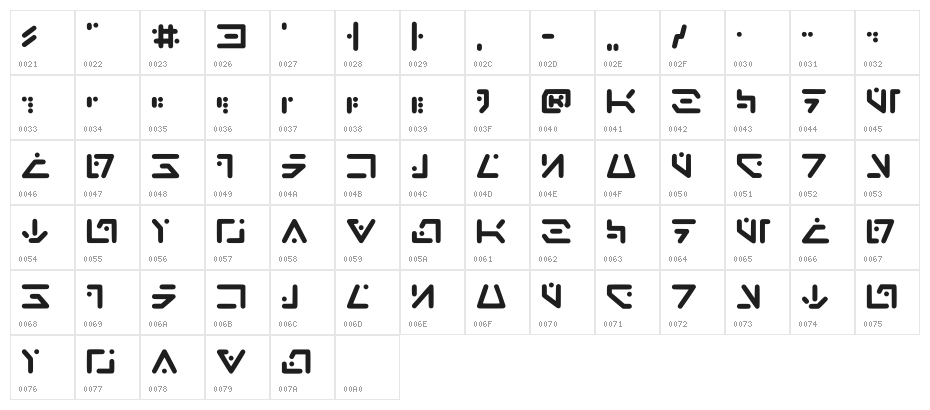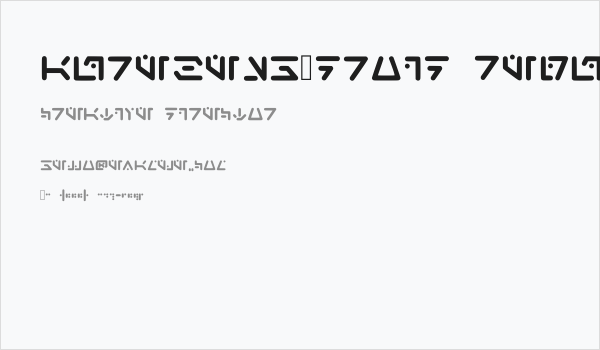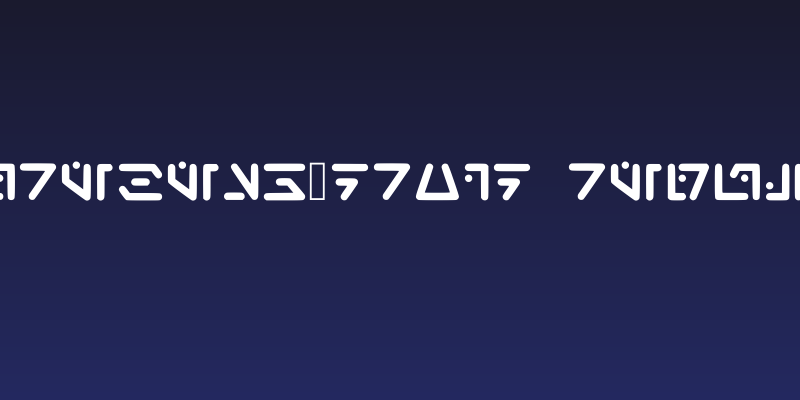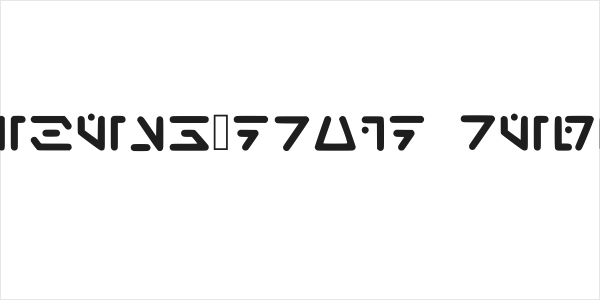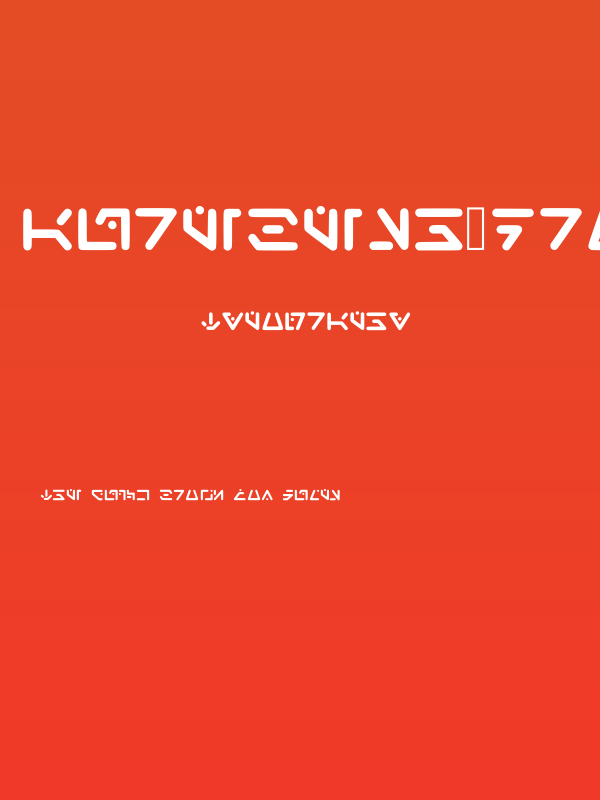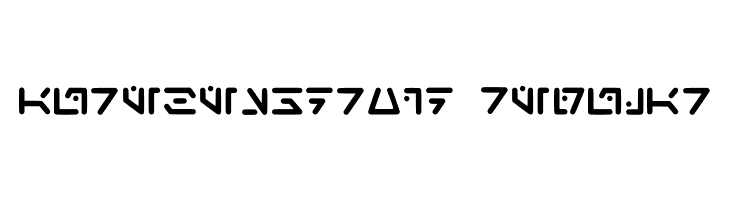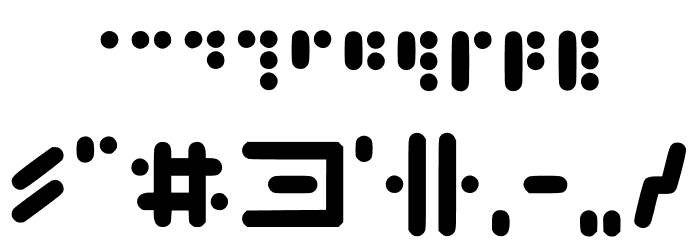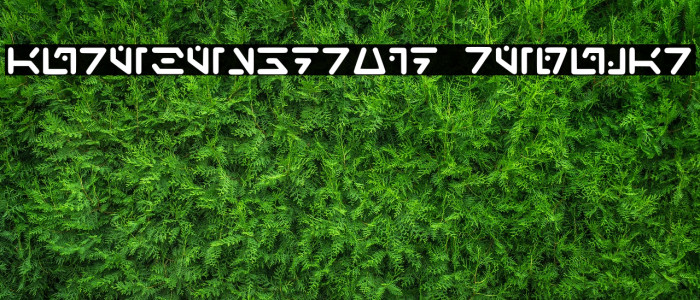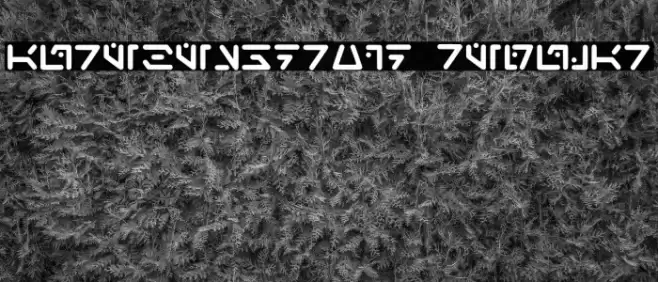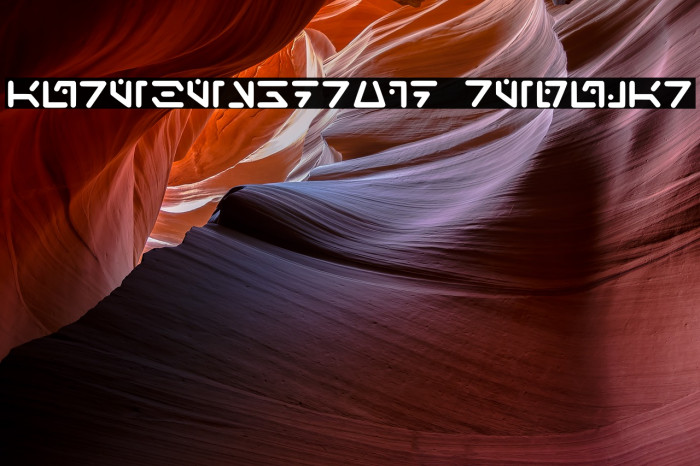
Aurebesh_droid Regular Font
| Estilo general | Futuristic |
| Caso de uso | Logos, Posters, Themed Interfaces |
| Proyectos propuestos | Ideal for science fiction themed projects, movie posters, video game interfaces, and any creative work requiring an alien or futuristic aesthetic. |
| Autor | Fonts by scratchones |